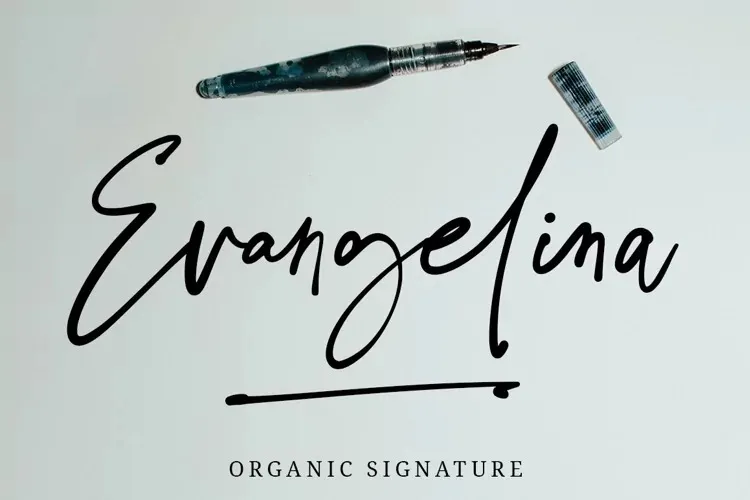
Evangelina Signature Font – Download Grátis
Essa font ‘Evangelina Signature’ é perfeitamente adequada para projetos que exigem charme e criatividade. Sua natureza casual-chic, escrita a mão, transmite um clima encantador, ideal para incorporar no seu trabalho. Criada pelo designer de fontes Typesthetic Studio, esta letra feita à mão está especialmente concebida para logos, cartões de aniversário e festas de casamento, envelopes de encomendas personalizadas, design fotográfico, marca d’água, embalagens de produtos e citações escritas a mão. Além disso, inclui 107 ligaturas escritas à mão, um conjunto completo de letras maiúsculas e minúsculas, símbolos multilíngues, números e pontuação. Sua versatilidade permite que você use essa fonte em uma ampla gama de projetos, sem perder o seu charme único.